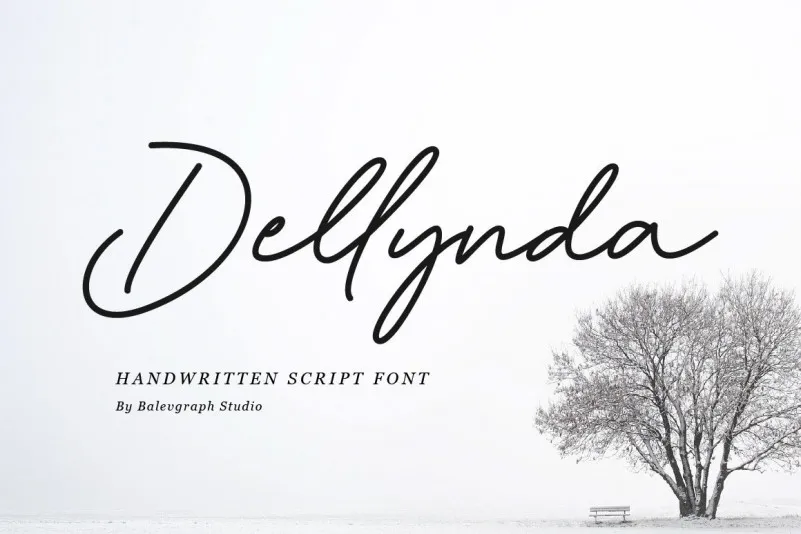
Dellynda Font – Download Grátis
A Dellynda Font é uma elegante e eterna fonte monoline com um toque de escrita humana, criada pelo design visionário do Balevgraph Studio. Suavemente impressionante, esta font oferece um toque suave e personalizado que se destaca em qualquer ambiente onde ela seja usada. Se você está procurando por uma maneira única de personalizar suas cartas de casamento ou invitations para festas especiais, a Dellynda é a escolha perfeita. Suas linhas finas e detalhes suaves deixam um impacto duradouro em qualquer design que você fizer. Da arte elegante das invitativas até o conteúdo vibrante dos posts na mídia social – sua versatilidade é limitada apenas pela criatividade de seu designer. Experimente a Dellynda Font para criar designs únicos e memoráveis.